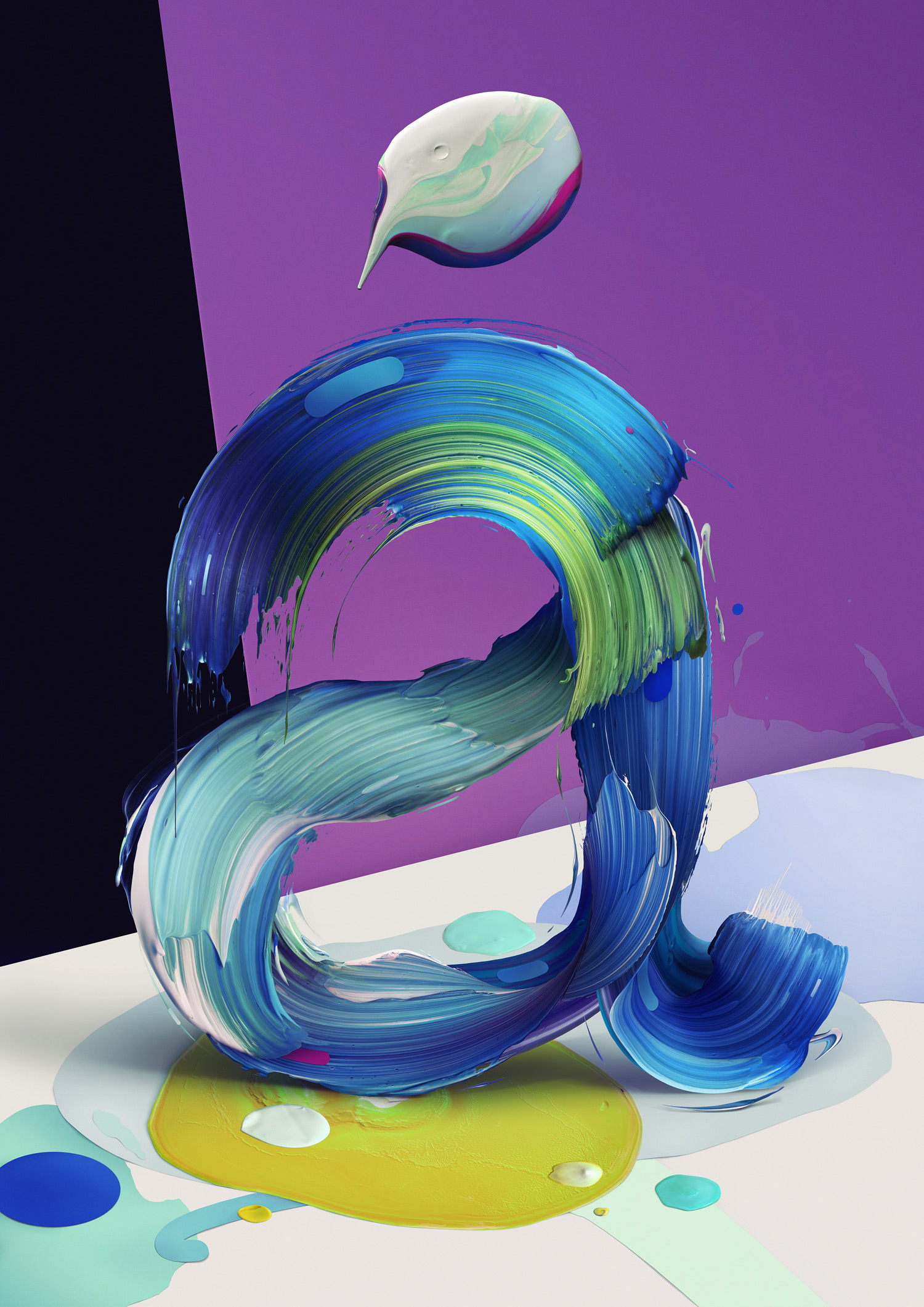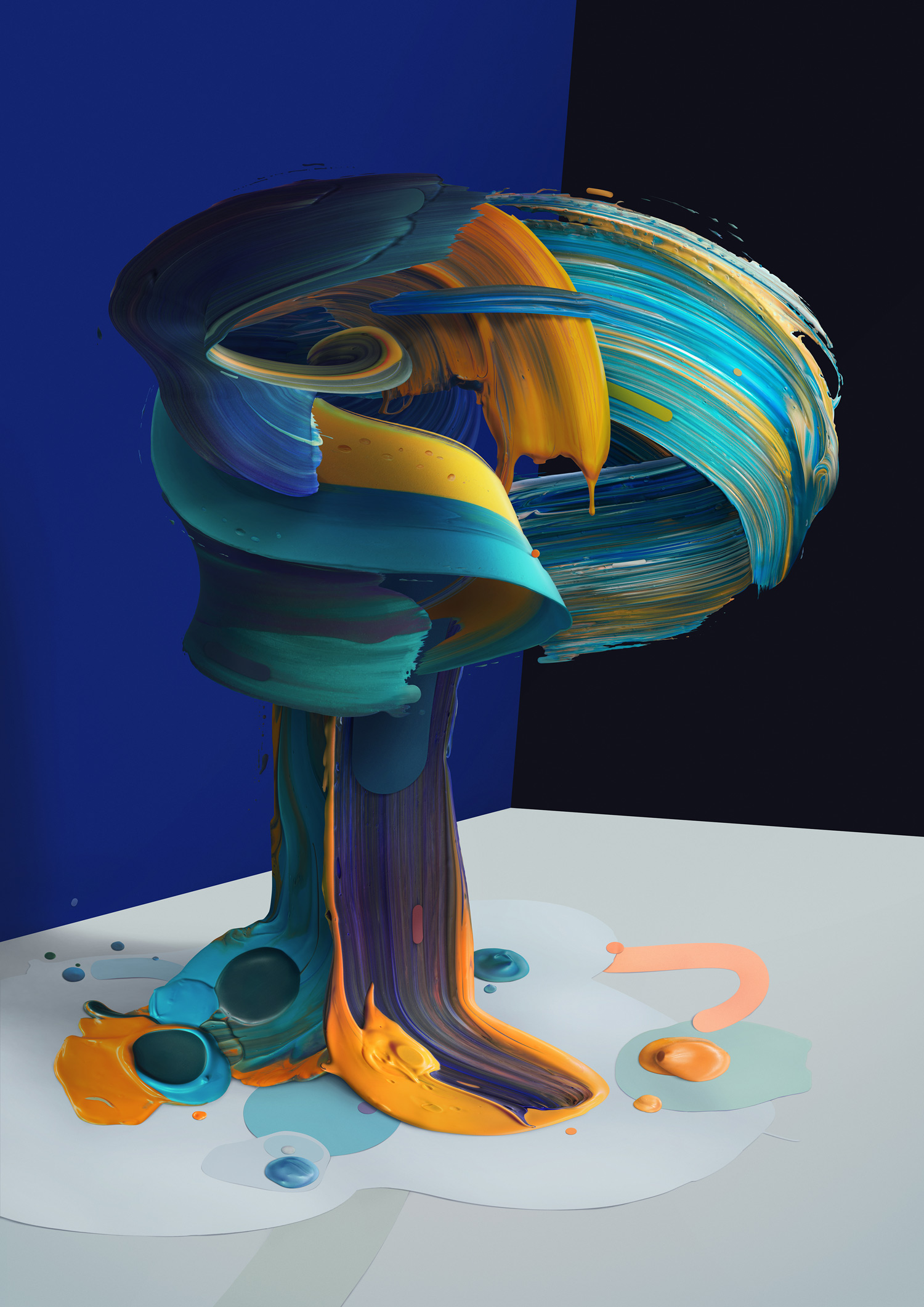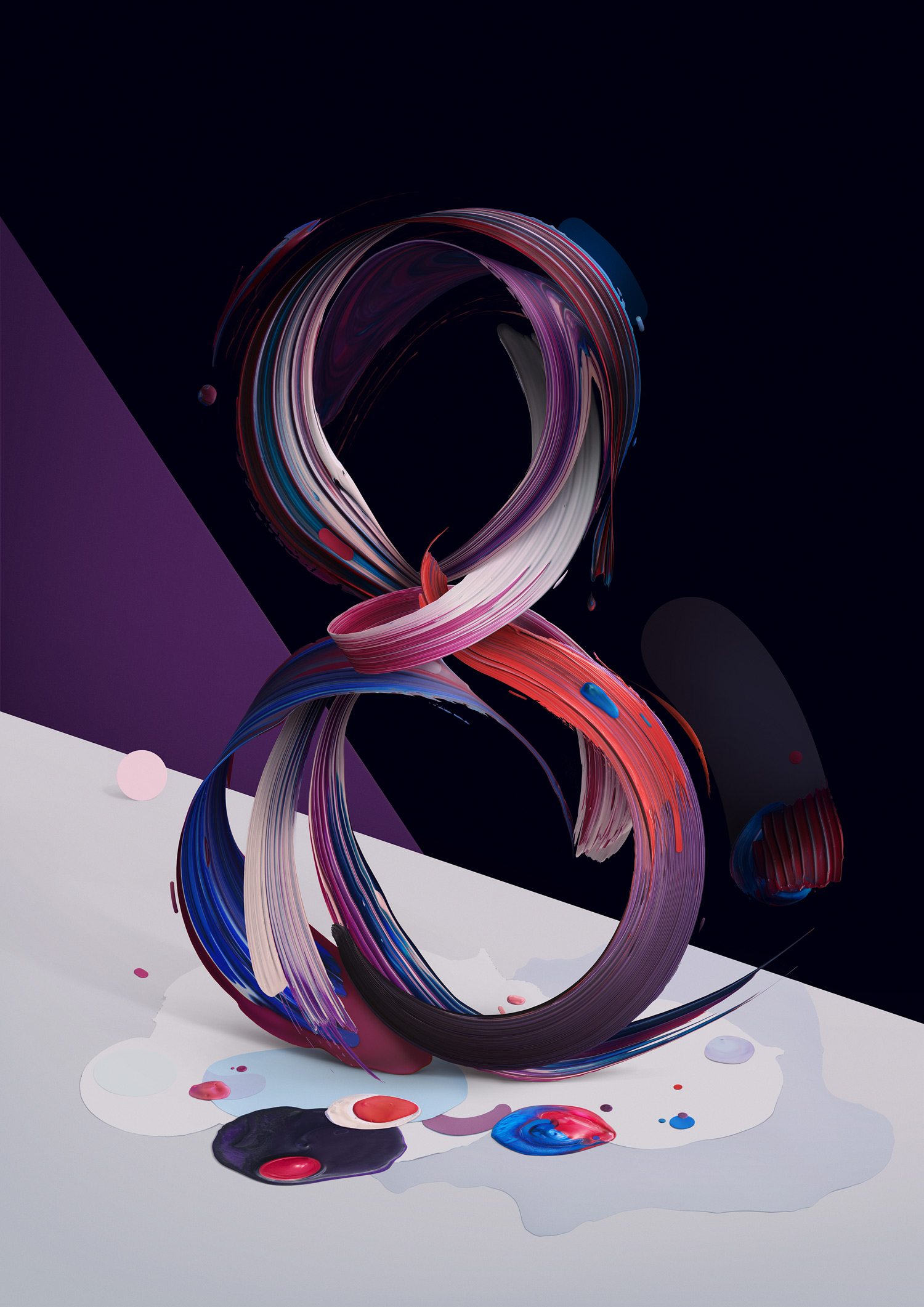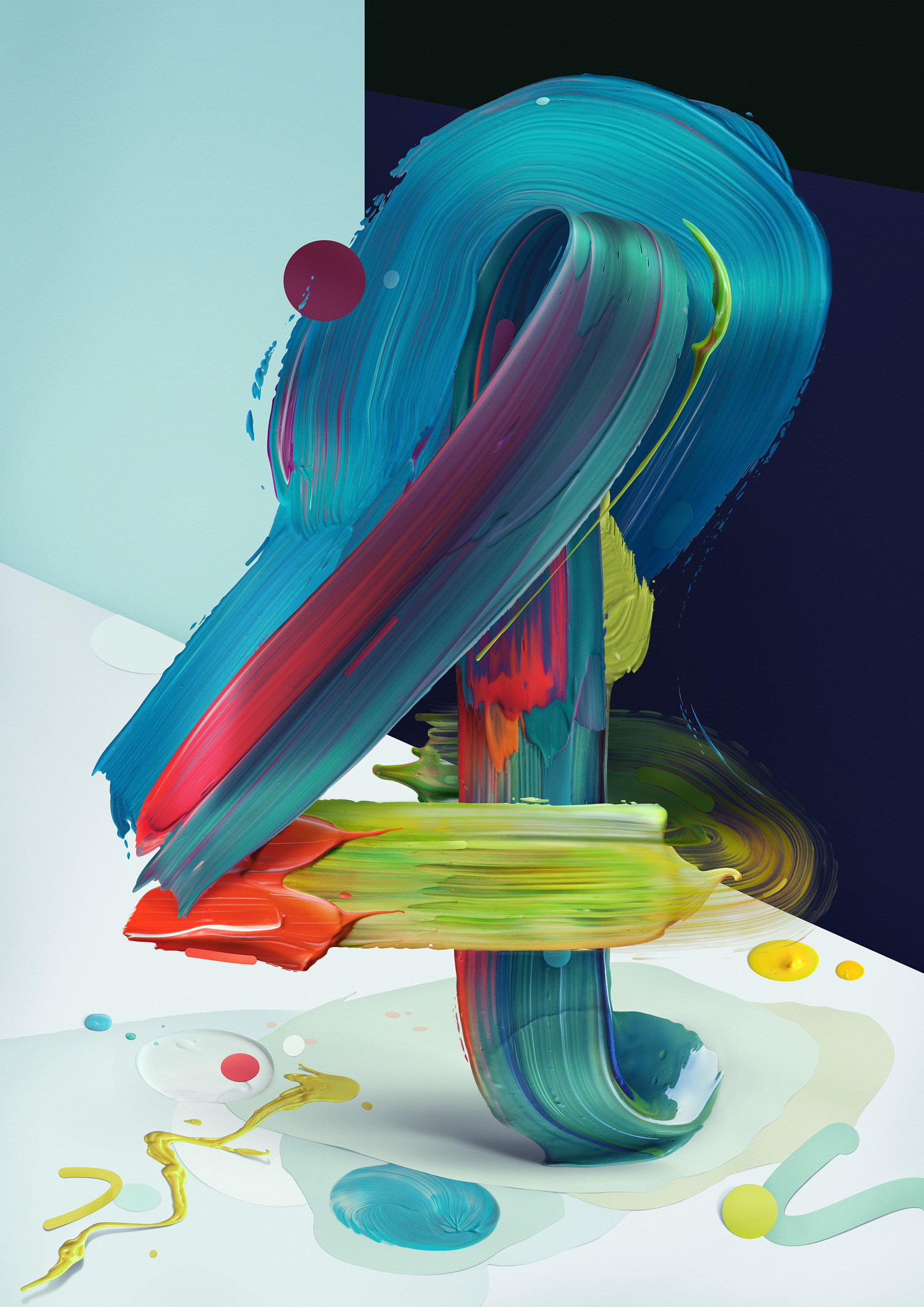
Typographie par Pawel Nolbert
Le designer Pawel Nolbert a crée des éclaboussures de peinture réels avec les techniques d’illustration numérique.
Son projet intitulé atypique, c’est un mélange de la peinture et de la typographie où le designer présente une série d’affiches comme une exploration de la forme et le rythme de lettres. Ainsi, ses œuvres d’art ont été construites à partir des gestes picturaux artistiques.